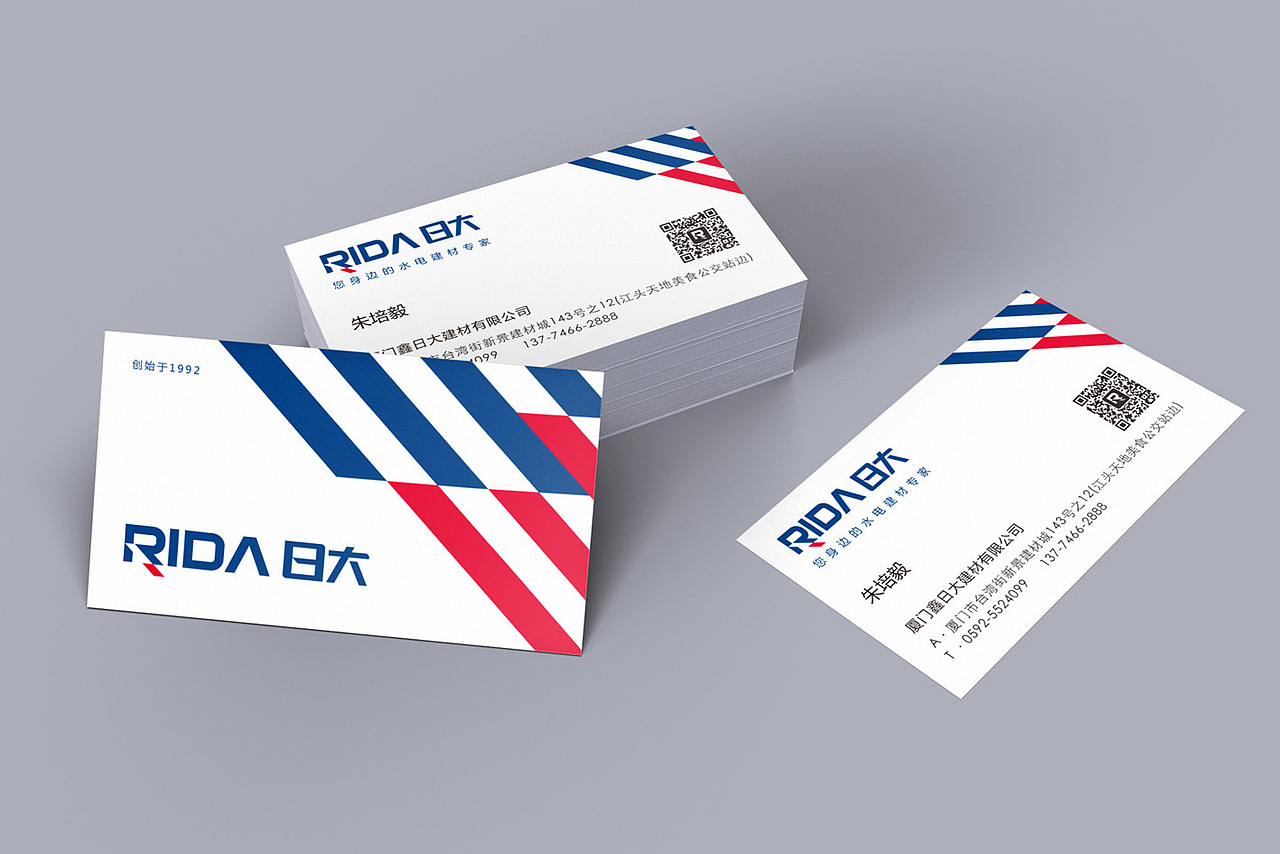
“日大水电”自1992年成立以来,
已有近30年的经营历程。
品牌以经营水电建材的批发及零售为主
一直秉承“价格公道、真材实料”的诚信经营理念,
在区域性已经有一定的知名度和市场份额。
在市场竞争愈演愈烈的当下,业主意识到品牌视觉的重要性...
在与业主的前期沟通中,我们发现他对美国公司、文化及产品的崇尚。
于是为了使“日大”品牌更国际化,我们以英文字体设计为主。<br>将首字母&quot;R&quot;右下角的笔画做了一个闪电状的斜角。增强品牌的视觉独特性<br>色彩的选用上,从美国星条旗色中抽离出红白蓝作为品牌主色<br>同时,蓝色象征了“水”,红色象征了“电”。二者与日大行业属性相吻合<br>
在与业主的前期沟通中,我们发现他对美国公司、文化及产品的崇尚。
于是为了使“日大”品牌更国际化,我们以英文字体设计为主。
将首字母"R"右下角的笔画做了一个闪电状的斜角。增强品牌的视觉独特性
色彩的选用上,从美国星条旗色中抽离出红白蓝作为品牌主色
同时,蓝色象征了“水”,红色象征了“电”。二者与日大行业属性相吻合
日大新logo的呈现,在建材行业中可谓首创,
它不仅有较强的视觉识别性,也有别于市面其他同类产品形象,<br>凸显其品牌个性的同时也增加了受众对于日大品牌的记忆点
日大新logo的呈现,在建材行业中可谓首创,
它不仅有较强的视觉识别性,也有别于市面其他同类产品形象,
凸显其品牌个性的同时也增加了受众对于日大品牌的记忆点